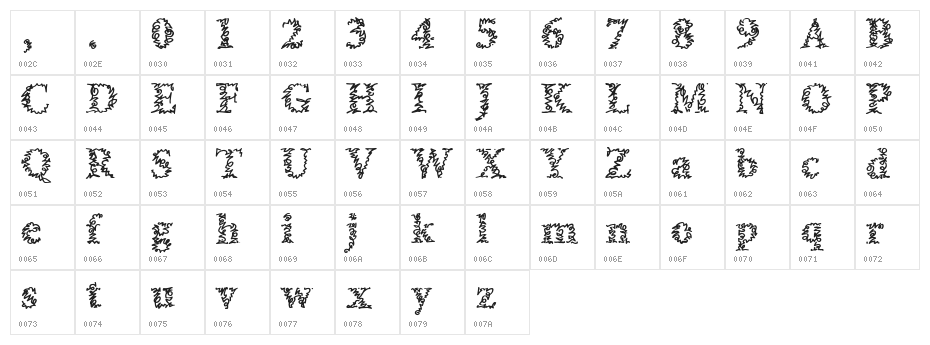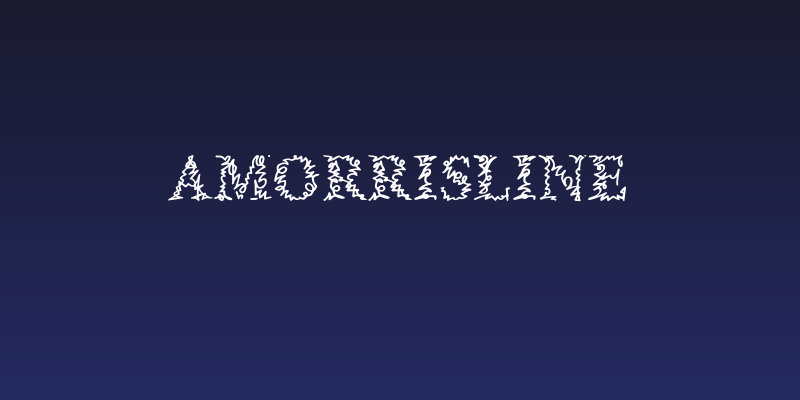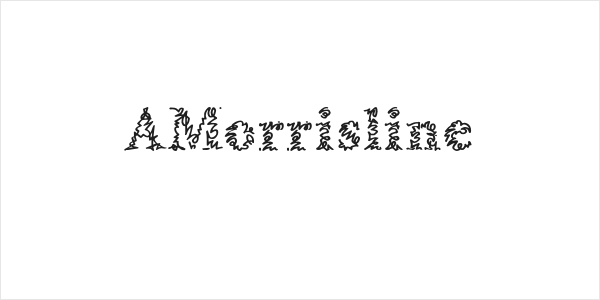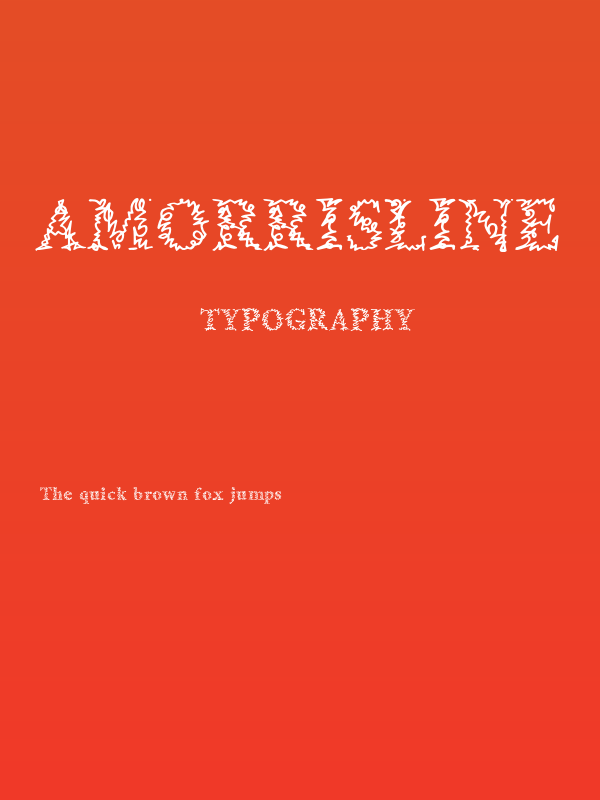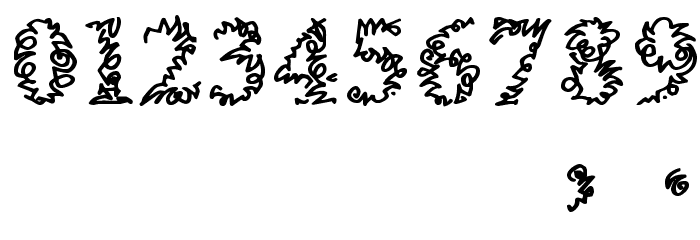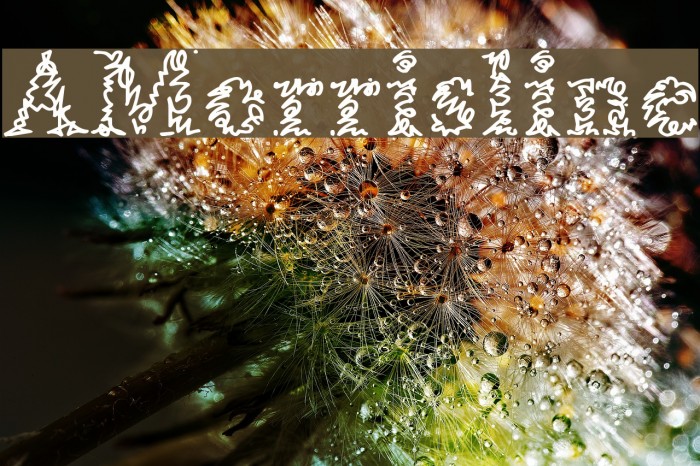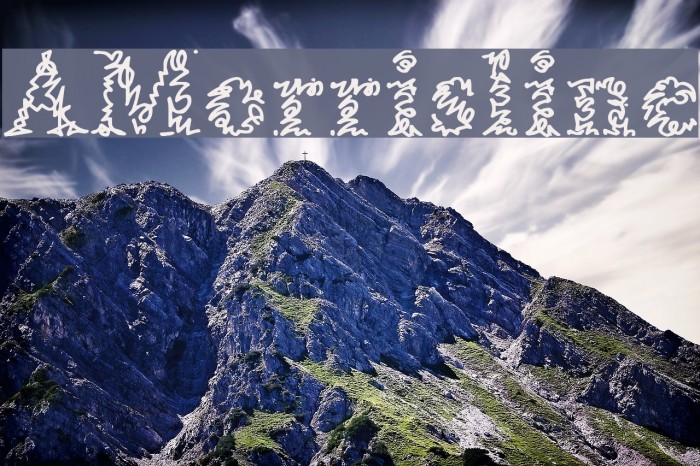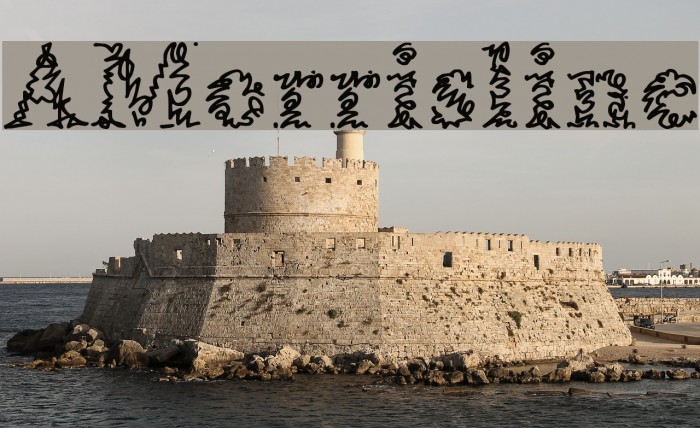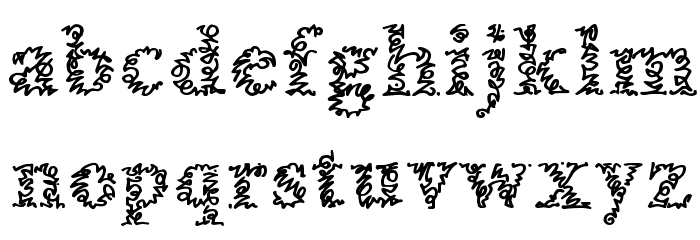
AMorrisline Font
| Anwendungsfall | Logos, Headlines, Artistic projects |
| Vorgeschlagene Projekte | Ideal for creative projects such as invitations, greeting cards, artistic posters, and branding materials that require a whimsical and decorative touch. |